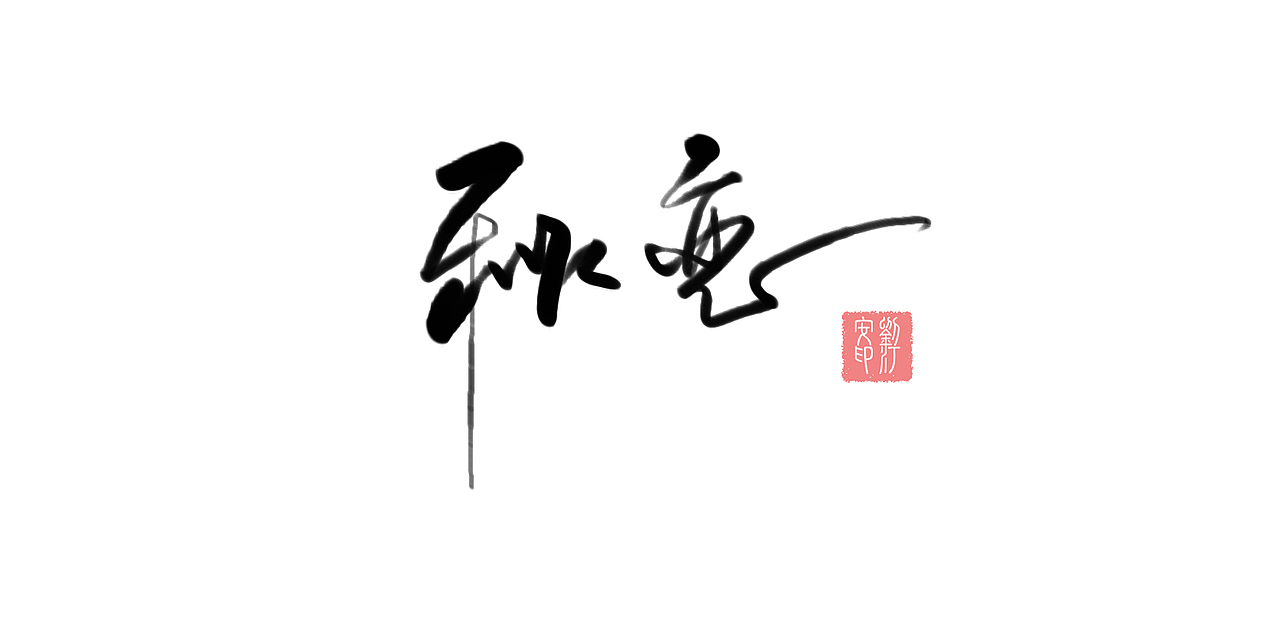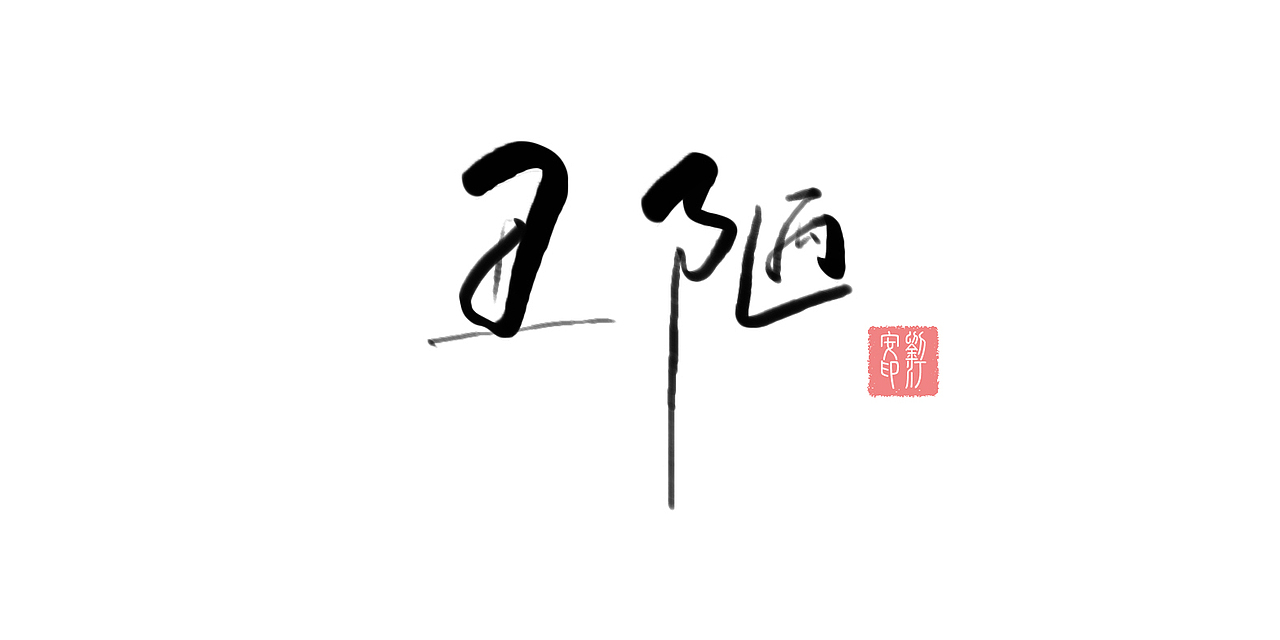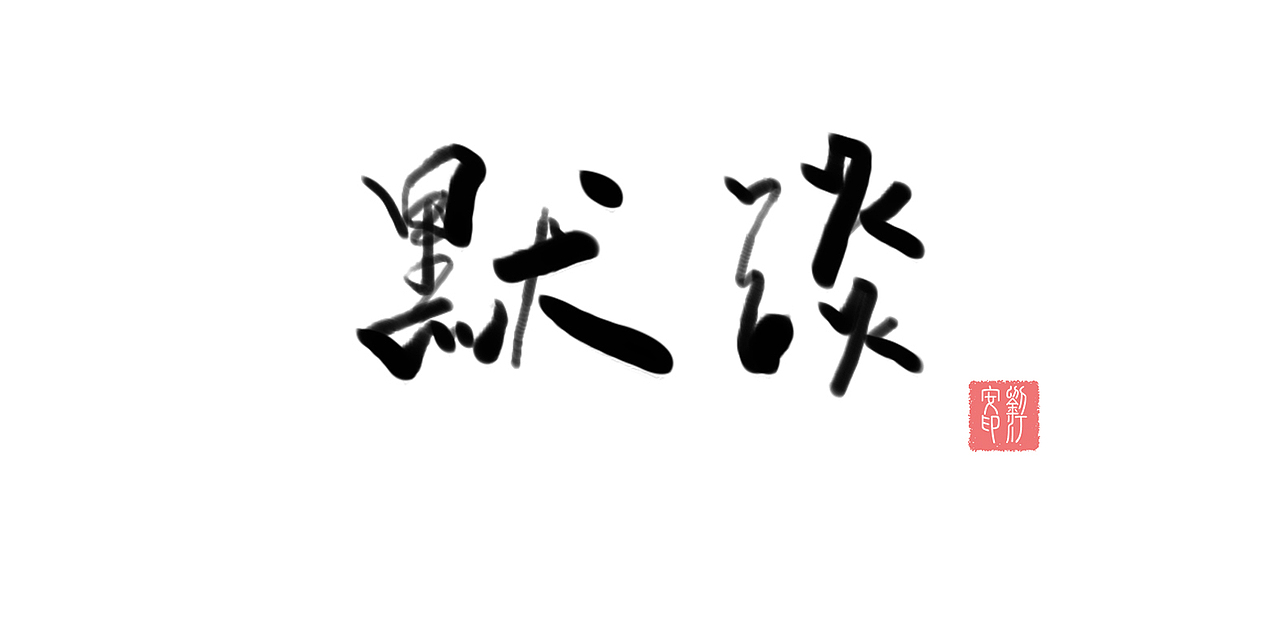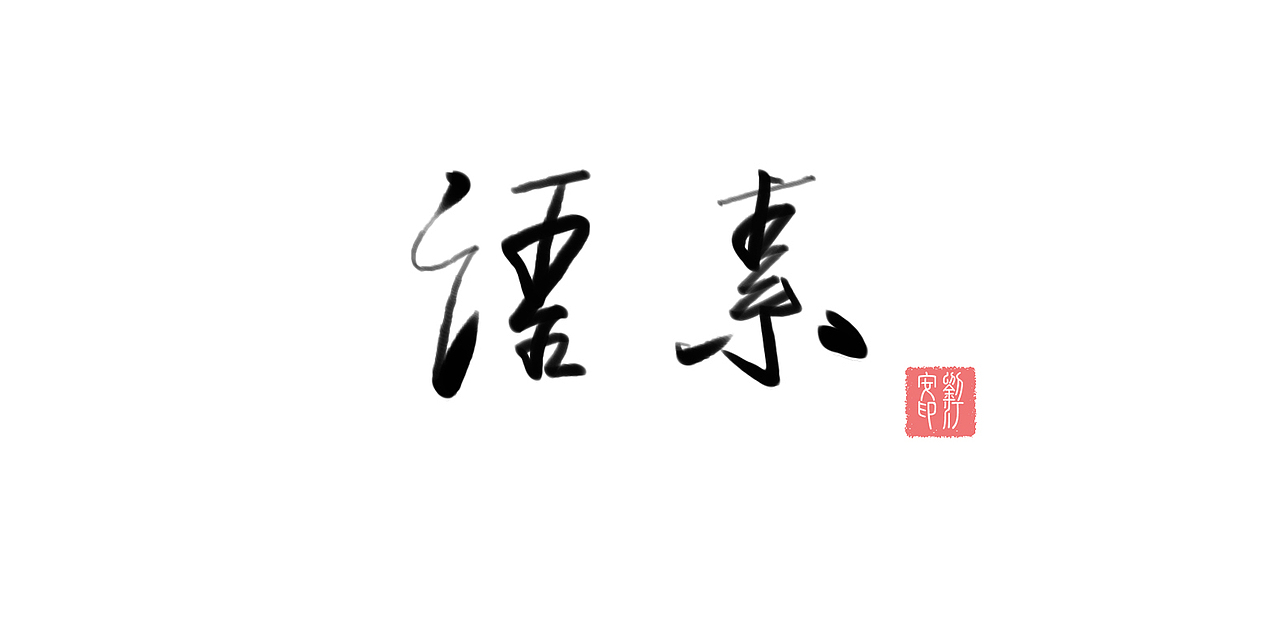
书法是中国及深受中国文化影响过的周边国家和地区特有的一种文字美的艺术表现形式。包括汉字书法、蒙古文书法、阿拉伯书法和英文书法等。其“中国书法”,是中国汉字特有的一种传统艺术。从广义讲,书法是指文字符号的书写法则。换言之,书法是指按照文字特点及其含义,以其书体笔法、结构和章法书写,使之成为富有美感的艺术作品。汉字书法为汉族独创的表现艺术,被誉为:无言的诗,无行的舞;无图的画,无声的乐等。--------------------------------------------------------------------------------------